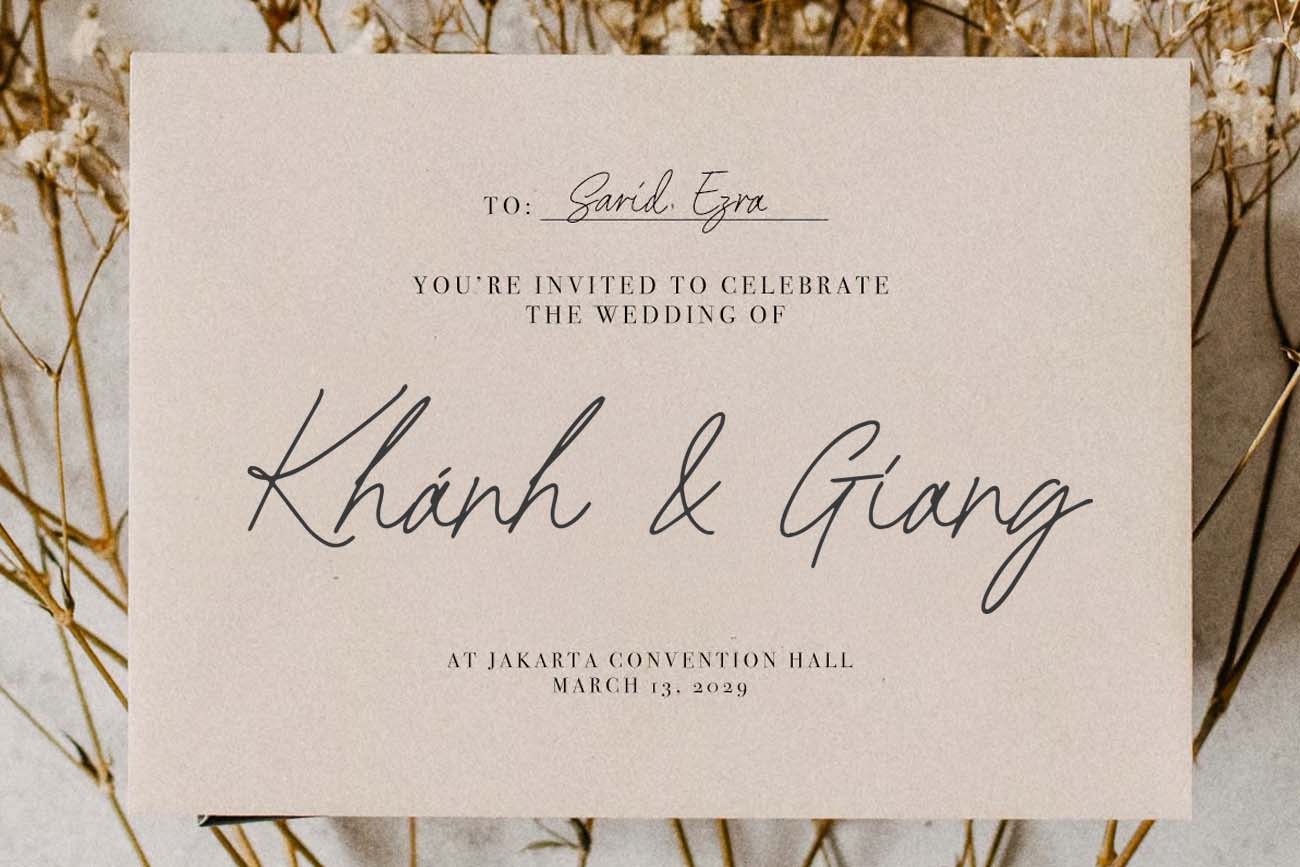
Siêu Phẩm Font Chữ Viết Tay Việt Hóa Dành Cho Designer - TH This Reality
Tác giả Letterhend
Trong giới thiết kế đồ họa và typography, việc tìm kiếm một font chữ viết tay mang đậm dấu ấn cá nhân, tự nhiên nhưng vẫn giữ được sự tinh tế luôn là một hành trình đầy thú vị. Hôm nay, hãy cùng khám phá TH This Reality – một bộ font chữ Việt hóa hoàn hảo được tinh chỉnh tỉ mỉ, hứa hẹn sẽ mang đến nguồn cảm hứng bất tận cho các dự án sáng tạo của bạn.
Khám Phá TH This Reality: Tuyệt Phẩm Font Chữ Viết Tay Việt Hóa Dành Cho Designer
Sức Hút Nguyên Bản Từ Font This Reality
Bản gốc của phông chữ này mang tên This Reality, được chắp bút bởi studio thiết kế danh tiếng Letterhend. Ngay từ khi ra mắt, This Reality đã gây ấn tượng mạnh mẽ với cộng đồng sáng tạo nhờ những đường nét phóng khoáng, nhịp điệu chữ uyển chuyển và chân thực như những nét mực viết tay trên giấy. Đây là sự lựa chọn lý tưởng cho các thiết kế mang hơi hướng hiện đại, cá tính như logo, bao bì sản phẩm, thiệp mời cưới, typography trích dẫn hay các ấn phẩm truyền thông mạng xã hội.
TH This Reality: Sự Giao Thoa Giữa Nghệ Thuật Và Tính Ứng Dụng
Nhằm mang vẻ đẹp của This Reality đến gần hơn với cộng đồng designer Việt Nam, TH Team đã dành trọn tâm huyết để nghiên cứu và phát triển phiên bản TH This Reality.
Điểm sáng giá nhất của bộ font chữ Việt hóa này chính là khả năng xử lý dấu tiếng Việt cực kỳ mượt mà. Đội ngũ TH Team đã khéo léo thêm thắt các dấu câu sao cho hài hòa tuyệt đối với hình dáng ký tự gốc. Nhờ đó, khi ứng dụng vào thiết kế, bạn sẽ có một font chữ viết tay tiếng Việt chuẩn xác, không bị gãy nhịp, không lỗi hiển thị mà vẫn giữ trọn vẹn được tinh thần tự do, bay bổng của tác giả Letterhend.